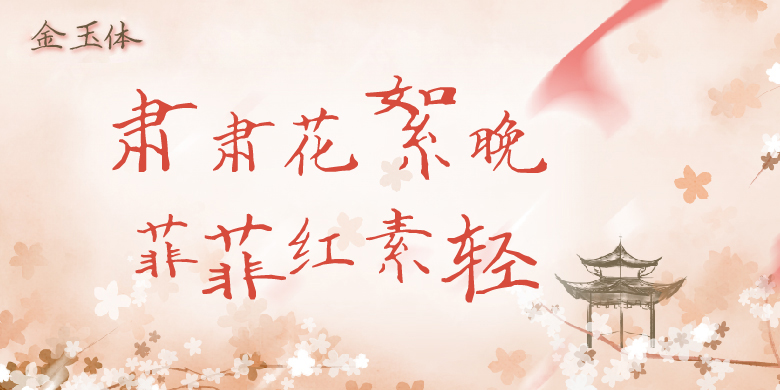
方正字汇-金玉体
字体品牌: 方正字汇 设计师:金玉 字体分类:常规书写·硬笔 字体属性:精品字 字符集:大陆简体(GB2312-80) 发布时间: 2019
形似楷体,端庄秀丽,笔力颇富弹性,温婉且朝气灵动,金雕玉琢,美观实用。适用于文艺类的书刊、品牌广告和产品包装设计,以及社交网络的个性化用字。